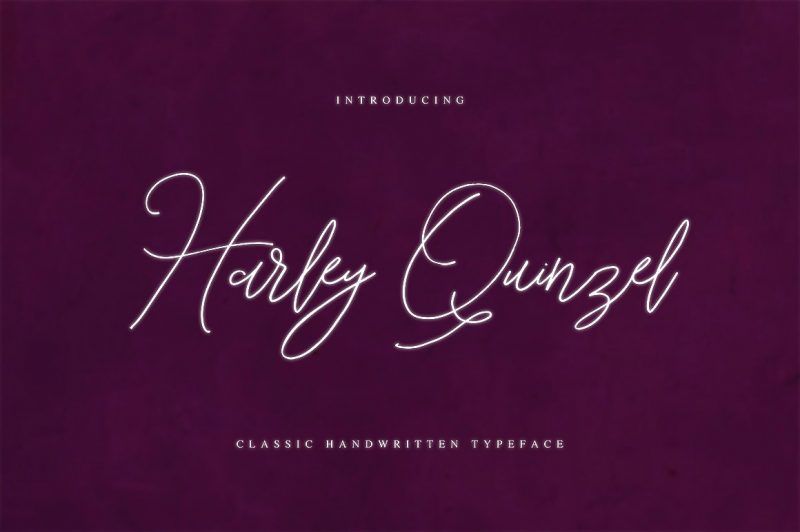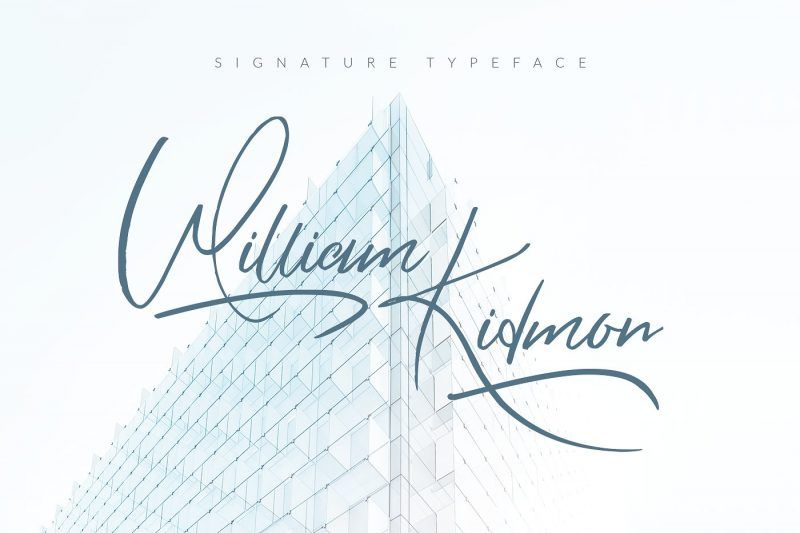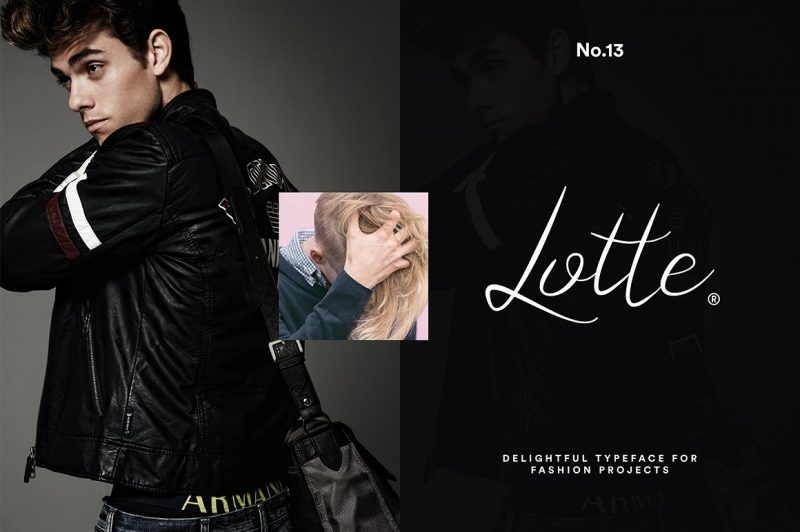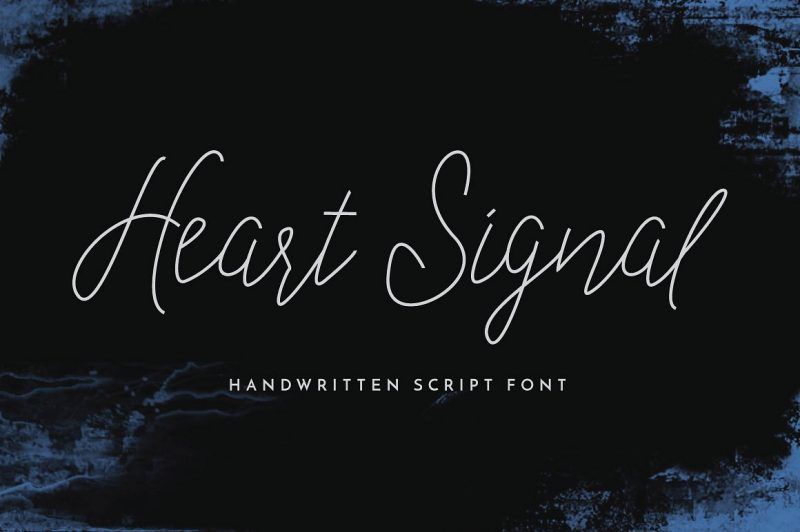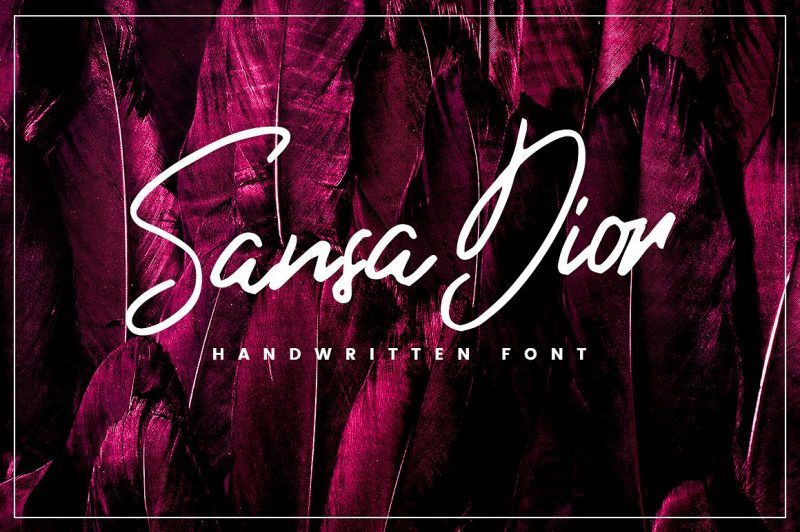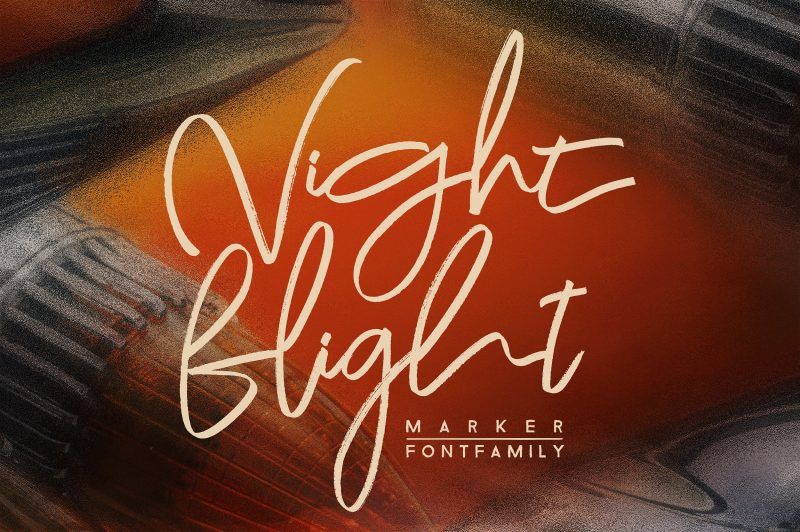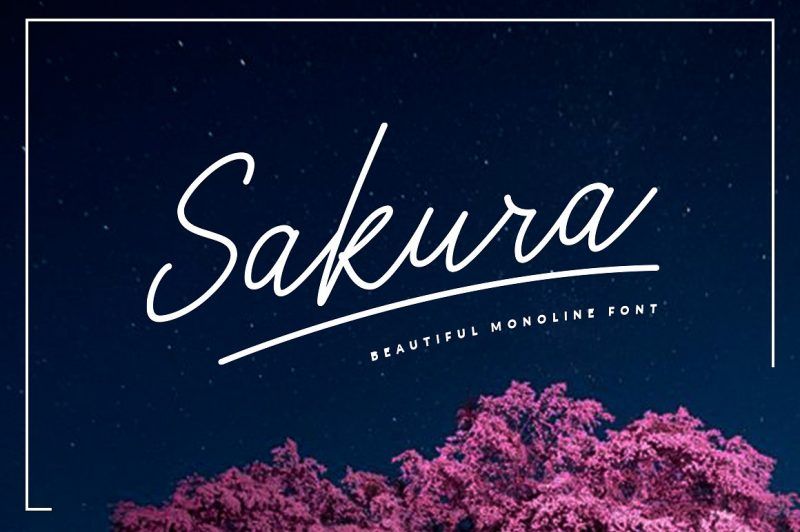
50 fuentes exclusivas para mejorar sus diseños
Con los conceptos de diseño que explotan aquí y allá, es importante mantenerse a la vanguardia. Para que su proyecto de diseño se destaque entre la multitud, necesita una fuente de firma que pueda mejorar aún más su trabajo.
1.  Hermes
La línea mono Hermes es el estilo de fuente hecho a mano que baila y luego traza en vivo para tener formas únicas de caligrafía, el estilo de escritura es muy natural.
Diseñada para una variedad de propósitos como logotipos, membretes, invitaciones, carteles e insignias, la línea mono Hermes es una fuente de estilo cursiva hecha a mano. Sus hermosas líneas y remolinos son ideales para cualquier forma de caligrafía.
2.  Guión de Hanni
Creado por Petra Burger, Hanni Script es una fuente manuscrita de estilo exclusivo. Es simple pero sofisticado y es una gran fuente para invitaciones de boda y cumpleaños.
3.  Enérgico preguntándose
Presentamos una de las mejores tan hermosas y viene con dos fuentes muy elegantes que están diseñadas para complementarse a la perfección.
Con dos elegantes fuentes creadas para funcionar perfectamente entre sí, Brisk Wondering es una elegante fuente manuscrita con hermosos rizos y silbidos. Es mejor para proyectos personalizados, tarjetas de felicitación y firmas de cartas.
4.  Guión Cityallir
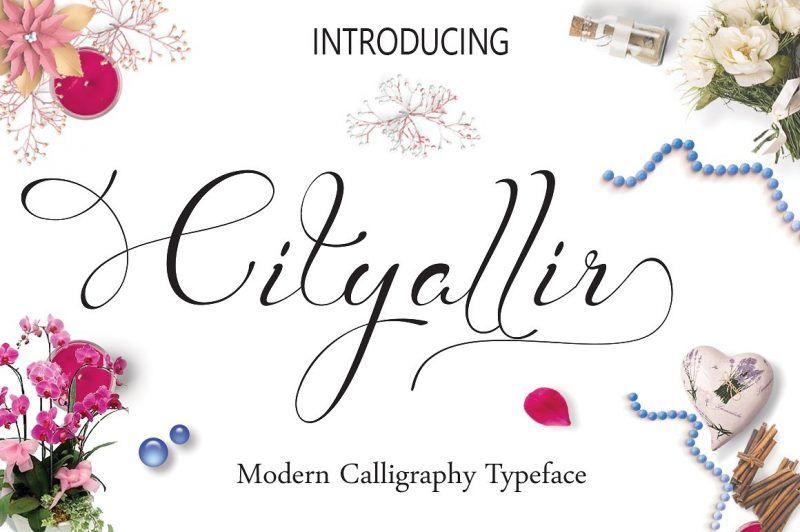
Cityallir Script: Es una caligrafía a mano, suave, moderna y clasik, caligrafía ondulada, que fue creada para satisfacer las necesidades de su próximo proyecto de diseño. Cityallir Script, se puede utilizar para diversos fines. tales como el título, firma, logo, correspondencia, invitaciones de boda, membretes, letreros, etiquetas, boletines, carteles, insignias, etc.
Diseñado para ayudar a calígrafos, diseñadores y artesanos a embellecer sus proyectos, Cityallir Script es una forma de caligrafía moderna y manuscrita. Sus magníficos trazos de letras son los mejores para señalización, etiquetas e insignias.
5.  Ajo
Garlic es una escritura de pincel que es hermosa y única, es un modelo de tipografías de caligrafía modernas, en combinación con un estilo de escritura de pincel de caligrafía.
Al igual que su interesante nombre, Garlic también es una fuente de escritura de pincel moderna y cautivadora. Su estilo hinchable y cursivo lo hace más divertido de usar en prácticamente cualquier proyecto de diseño.
6.  Guión de arroz gullami
Gullami Rice Script es el tipo de letra original, que era tan fresco y natural.
Una fuente de escritura original, Gullami Rice Script está destinada a numerosos propósitos de diseño, como citas impresas, invitaciones personalizadas, productos de empaque y títulos de revistas, entre otros.
7.  Guión de pelirrojas
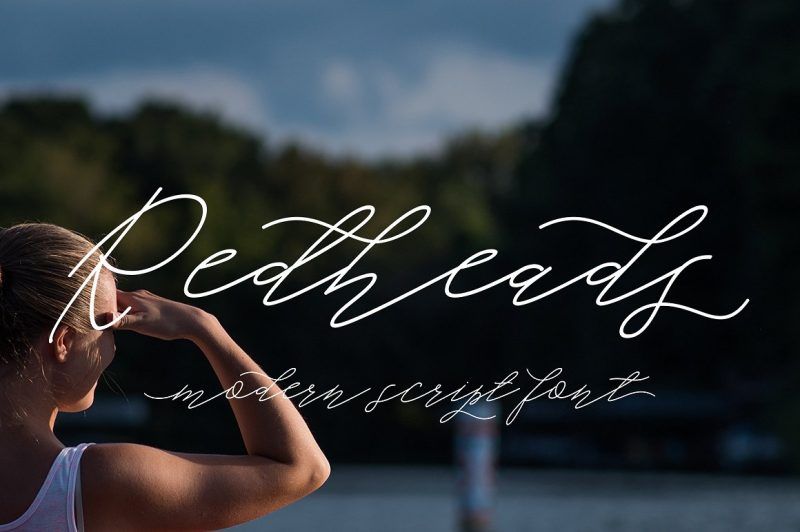
Redheads Script es un hermoso manuscrito caligráfico moderno, espero que te interese esta fuente, dinámica y bonita con swashes. Puede usarse para muchos propósitos. tales como título, firma, logotipo, invitaciones de boda, membretes, señalización, etiquetas, boletines, carteles, insignias, etc.
Con sus elegantes remolinos y líneas cursivas, Redheads Script es una hermosa fuente caligráfica. Es lo mejor para proyectos de diseño femenino como una invitación a una fiesta de cumpleaños de 16 años o una tarjeta de felicitación personalizada.
8.  Tipografía bonita
Jolies son fuentes modernas y elegantes escritas a mano, que combinan desde el tipo de letra clásico al moderno con una línea de base de diseño limpio. Se puede utilizar para diversos fines, como títulos, firmas, logotipos, invitaciones de boda, camisetas, membretes, carteles, etiquetas, noticias, carteles, insignias, etc.
Diseñado por Maulana Creative, Jolies Typeface es una fuente cursiva manuscrita moderna. Combina lo mejor de los tipos de letra clásicos y contemporáneos resaltados por una línea de base de diseño sin complicaciones.
9.  Fuente Yusuf Kral Artistica
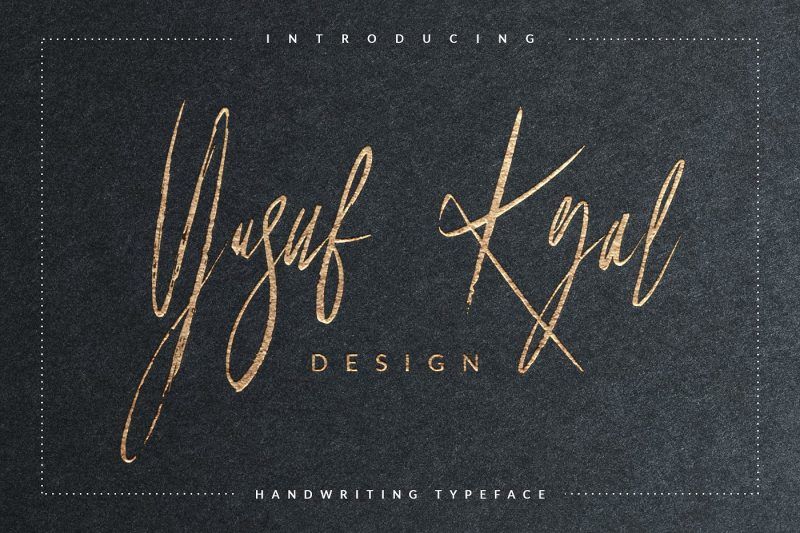
La fuente Yusuf Kral artistica es una fuente hecha a mano creada con un pincel grueso. Es una fuente de firma que el grosor de las líneas es encantador. Se puede usar fácilmente para camisetas, bolsos, invitaciones, etc. Cada vez es más interesante con personajes especiales.
Con su característica de pincel grueso, Yusuf Kral Artistica es una fuente cautivadora y nítida hecha a mano. Se utiliza mejor para camisetas, bolsos y citas impresas.
50.  Firma Otella
Presentamos Otella Signature Typeface, una fuente que es muy fresca y con un estilo único hecho a mano.
Con su estilo hecho a mano fresco y único, Otella es la fuente adecuada para hacer que cualquier diseño sea más llamativo. La fuente cursiva es la mejor para el diseño de maquetación, el eslogan y los logotipos.
Con estos asombrosos fuentes de firma , puede hacer que su diseño se destaque fácilmente por encima del resto.